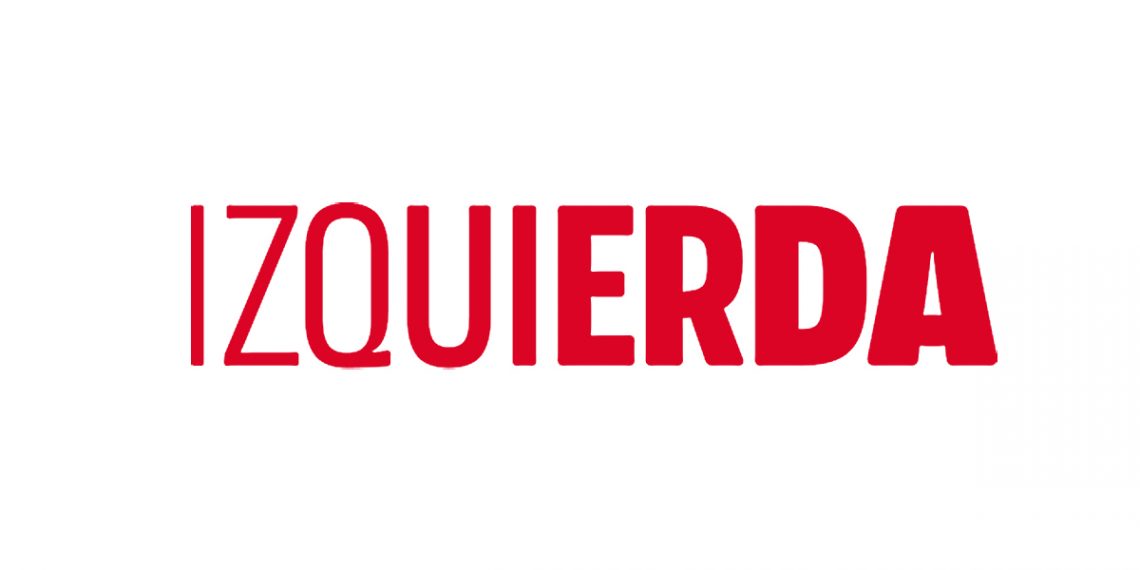
Izquierda Unida diseña su propia tipografía
Cada vez son más las marcas de grandes compañías que apuestan por la creación de una tipografía propia con la que poder comunicarse con voz propia e identificativa —como Ericsson, Samsung, el Banco Santander o IBM—. Una tendencia a la que ahora se suma la organización política Izquierda Unida. Aunque todavía está en fase beta, ya se vislumbra qué aspecto tendrá y hacia dónde se dirige. Con el objetivo de saber un poco más sobre esta tipografía, hablamos con Alejo Sanz, coordinador del área de comunicación y diseño de Izquierda Unida y con Pablo Gámez, diseñador de tipografías quien se ha encargado de la parte técnica de este proyecto.
Tipografía de Izquierda Unida todavía en desarrollo.
Es muy probable que estemos ante la primera tipografía propia de un partido político español, ¿es así?
Alejo Sanz: La verdad es que no tenemos noticias de que en España se haya desarrollado una tipografía en exclusiva para un partido político. Aunque, si hablamos de fuera de España, estamos seguros de que sí hay casos.
¿Cómo surge el proyecto?
AS: Al ser el responsable que coordina el área de comunicación de Izquierda Unida y además tener la responsabilidad de la parte gráfica de la campaña y de la organización, siempre había querido una tipografía propia para la organización. Era un deseo que siempre habíamos tenido. Al equipo nos parecía muy interesante hacerlo realidad ya que con ella, se aportaría al universo de la comunicación política un elemento que nunca se había hecho y que es muy interesante en términos políticos y en términos de diseño.
Lo de tener una tipografía propia, más allá del gusto de tenerla y de incluirla en el proceso, tiene un sentido político también.
Lo que te permite es tener una voz propia. Es un elemento más a unir a los que te identifican gráficamente, como un logotipo; un elemento que te identifica políticamente. Por eso nos parecía muy interesante esta apuesta.
¿Cómo se incorpora Pablo Gámez?
Pablo Gámez: He tenido inquietudes políticas desde hace tiempo. Me interesa la política y los movimientos sociales. Además, tengo amigos relacionados con Izquierda Unida, quienes me presentaron a Alejo Sanz. Por eso, en el momento que encontré un hueco entre trabajo y trabajo, me reuní con Alejo para ver cómo podíamos colaborar. Empezamos a trabajar juntos y de ahí a que este proyecto surgiera de manera totalmente natural. En un momento dado, Alejo me habló de que a la organización le vendría muy bien tener una tipografía propia y me sumé a la propuesta sin dudarlo.
Para Izquierda Unida no tenía sentido seguir utilizando tipografías que puede utilizar cualquier persona, sobre todo teniendo en cuenta que se trata de una organización política que tiene unas ideas propias, que le da mucha importancia a su programa político a pesar de ir en coalición, y que se preocupan de tener una opinión. Tenía mucho más sentido crear una tipografía con una voz propia y que la militancia pudiera usar.
¿Cuánto tiempo ha pasado desde que decidís crearla hasta ahora que tenéis esta versión beta?
AS: Fue a principios de año cuando nos planteamos el proyecto. Fue entonces cuando iniciamos la fase de investigación en la que empezamos a buscar referencias. En cuanto a la parte técnica, Pablo lleva trabajando en la tipografía y desarrollándola un par de meses.
Con el adelanto electoral nos surgió un problema en los tiempos de desarrollo del proyecto. La tipografía estaba pensada para lanzarse de cara a la campaña que estaba convocada originalmente a finales de mayo de este año, pero al hacer el adelanto electoral se nos trastocaron los planes.
Queríamos tener la tipografía lo más avanzada posible para la campaña, pero al final lo que hemos tenido que hacer con este adelanto electoral es una liberación de un par de pesos para poder cubrir la demanda de esta campaña.
PG: Y, además, la realidad de la campaña es muy dura. Es la primera vez que estoy trabajando en una campaña electoral y resulta bastante complejo combinar el trabajo de diseño de piezas dentro del equipo de comunicación de la organización con el desarrollo de la tipografía.
AS: Como Pablo se ha incorporado en el equipo gráfico de la campaña y ha estado trabajando en la gráfica, no ha podido desarrollar el trabajo tipográfico como lo teníamos previsto.
Tipografía de Izquierda Unida todavía en desarrollo.
¿Cuándo se presentará oficialmente la nueva tipografía de Izquierda Unida?
AS: Tenemos pensado presentar la tipografía hacia el 10 de mayo. Queremos convertirlo en un hito de campaña porque queremos vincular la presentación de la tipografía con la campaña. Es una noticia política y también es una noticia interesante desde el punto de vista del diseño gráfico.